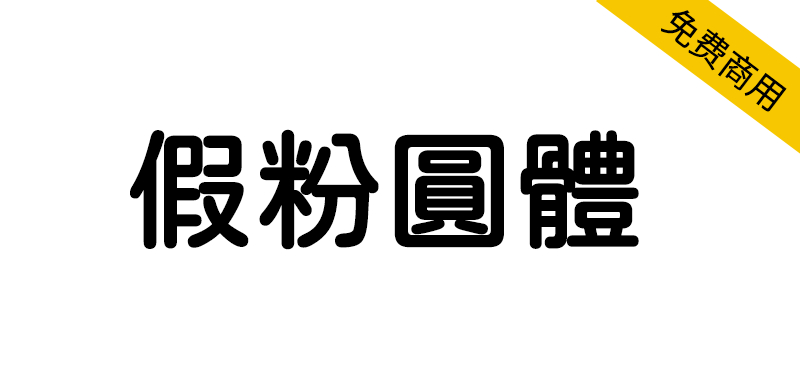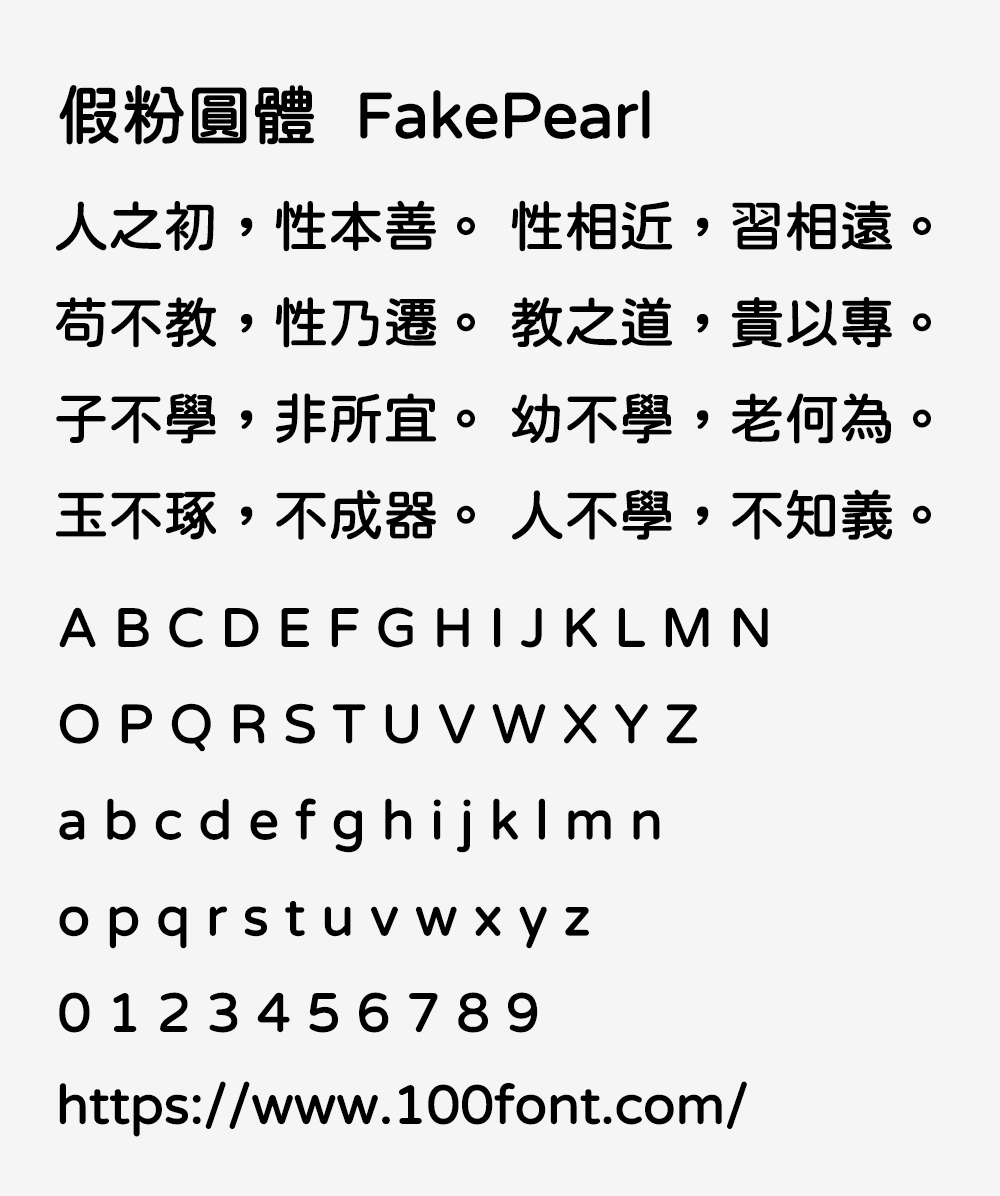
假粉圆体是基于jf open 粉圆的开放原始码中文字型,调整一下字的粗细(ExtraLight、Light、Regular、Medium、SemiBold),并重新放到网上让大家下载。
原本的粉圆字体放在Regular 字重里,通过程序自动产生ExtraLight、Light、Medium、SemiBold 新的字重。
在ExtraLight和Light字重是把原本的粉圆字体微微调细一点点。在Light的字重里,可能会因为笔划太细造成某些笔画消失。
在SemiBold和Medium的字重里,可能会因为笔划太粗造成某些笔画重叠难以识别,有粗体字的需求,可以先挑战使用SemiBold字重看看,如果发现效果不如预期,Medium字重。
不能确定自动产生出来的字重里每一个都是完整的字,毕尽程序会误判是常有的事情,所以不是在Regular字重里的笔划可能会消失。